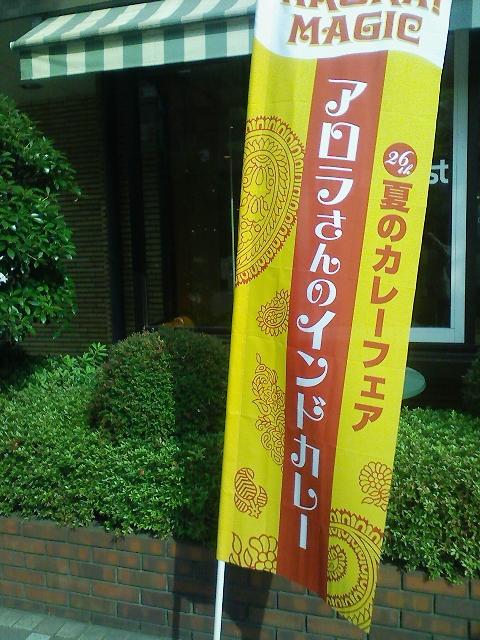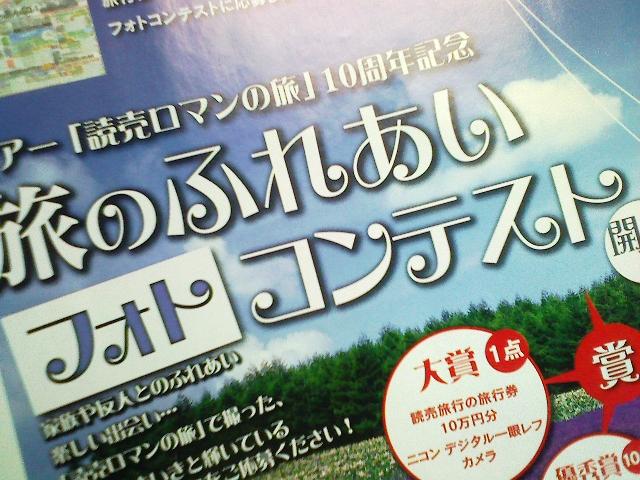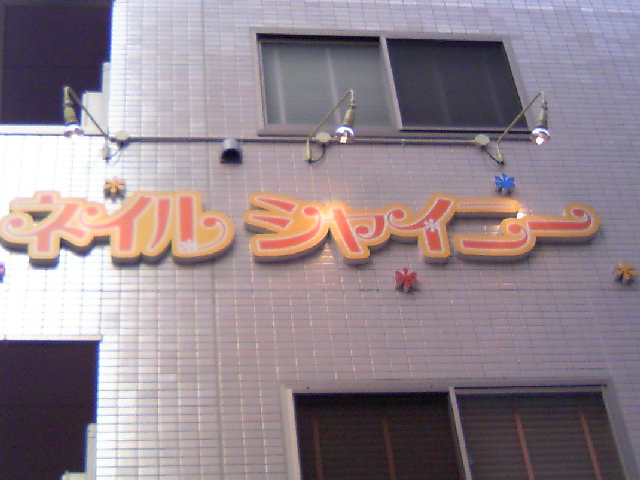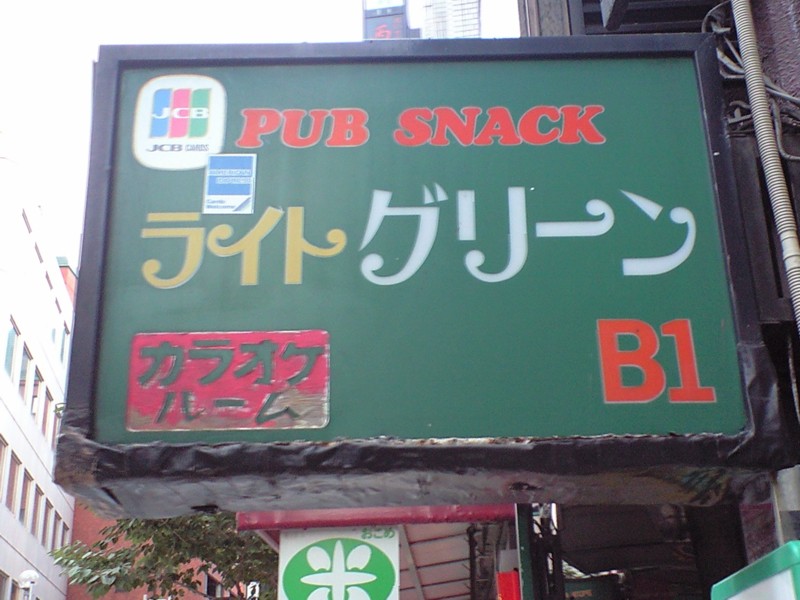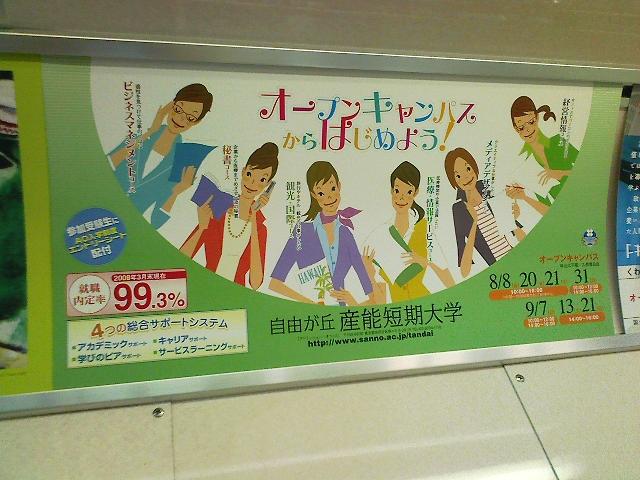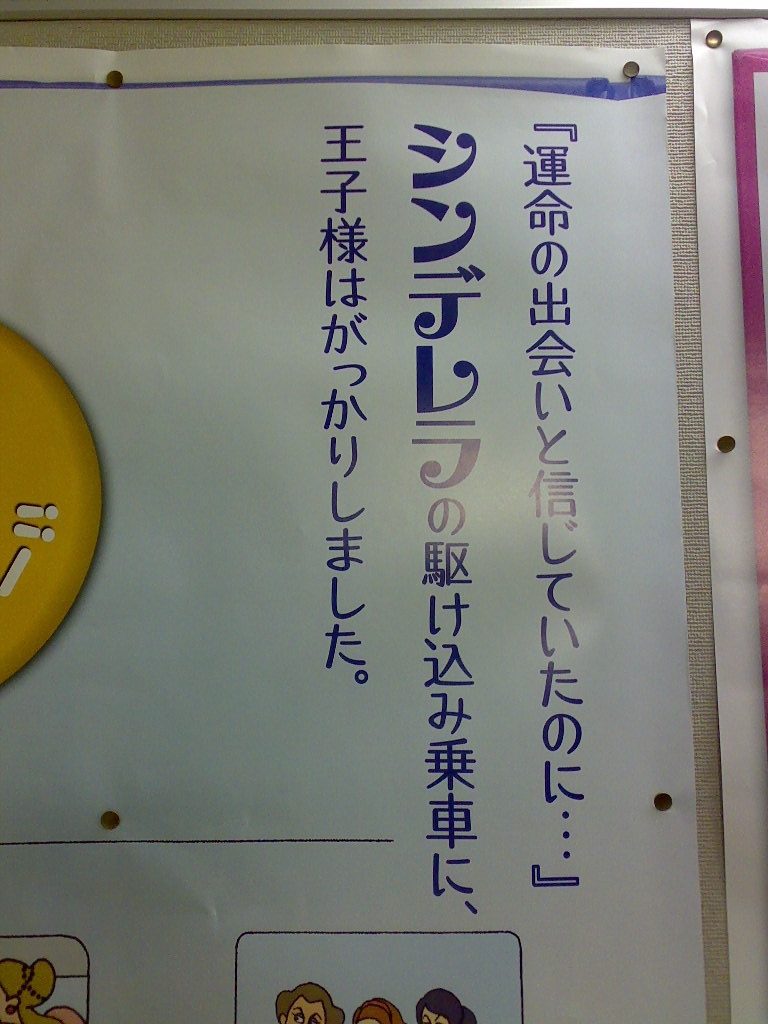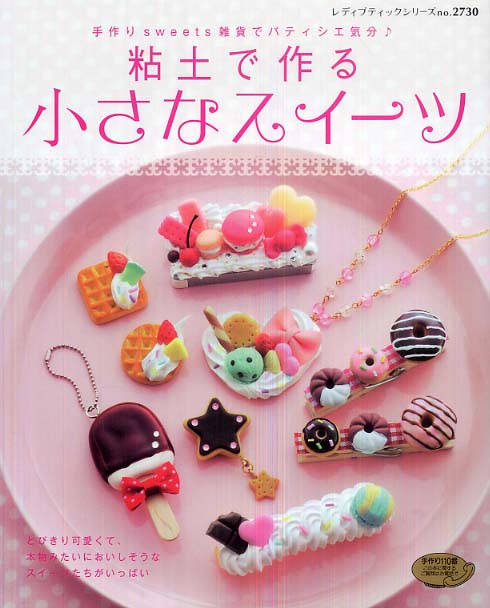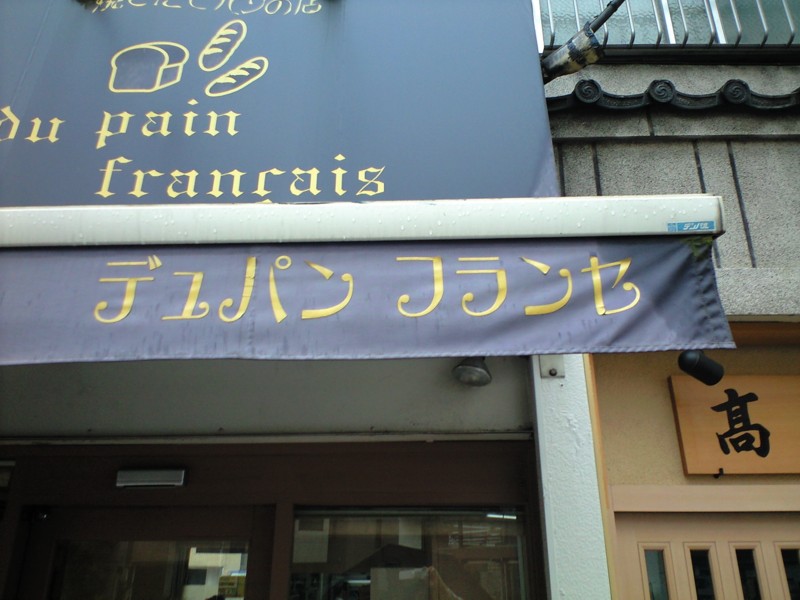
かわいいです。
「リストランテ・パラディーゾ」というアニメが放送していたようですが、
こちらのロゴはえれがんとが元なのでしょうか?
●部分が消されて不自然な感じに見えますが。
確かに、えれがんとを元にアレンジしたように見えますね。
不自然か不自然でないか、どちらにしても
そのロゴを作った人の好みなんでしょう。
漫画雑誌の次号予告ページで。
メインタイトルの「グアム」は墨東書体ですが。
新聞のテレビ欄に掲載されていた、TBSテレビの番宣広告です。
「ク」の文字の最後の部分が少し長く伸ばされています。
何の効果も生んでいないと思うけれど…?
女性向けコミック雑誌で見つけました。
書名:お金持ちはキレイ好き!
「は」の文字はすこしイジラレてるようだ…。
一部抜粋。
多少デフォルメはありますが、いかにもという感じです。
書名:しあわせぷーどるず
女性向けコミック誌の人気連載マンガだそうです。
濁点などに手が加えられています。